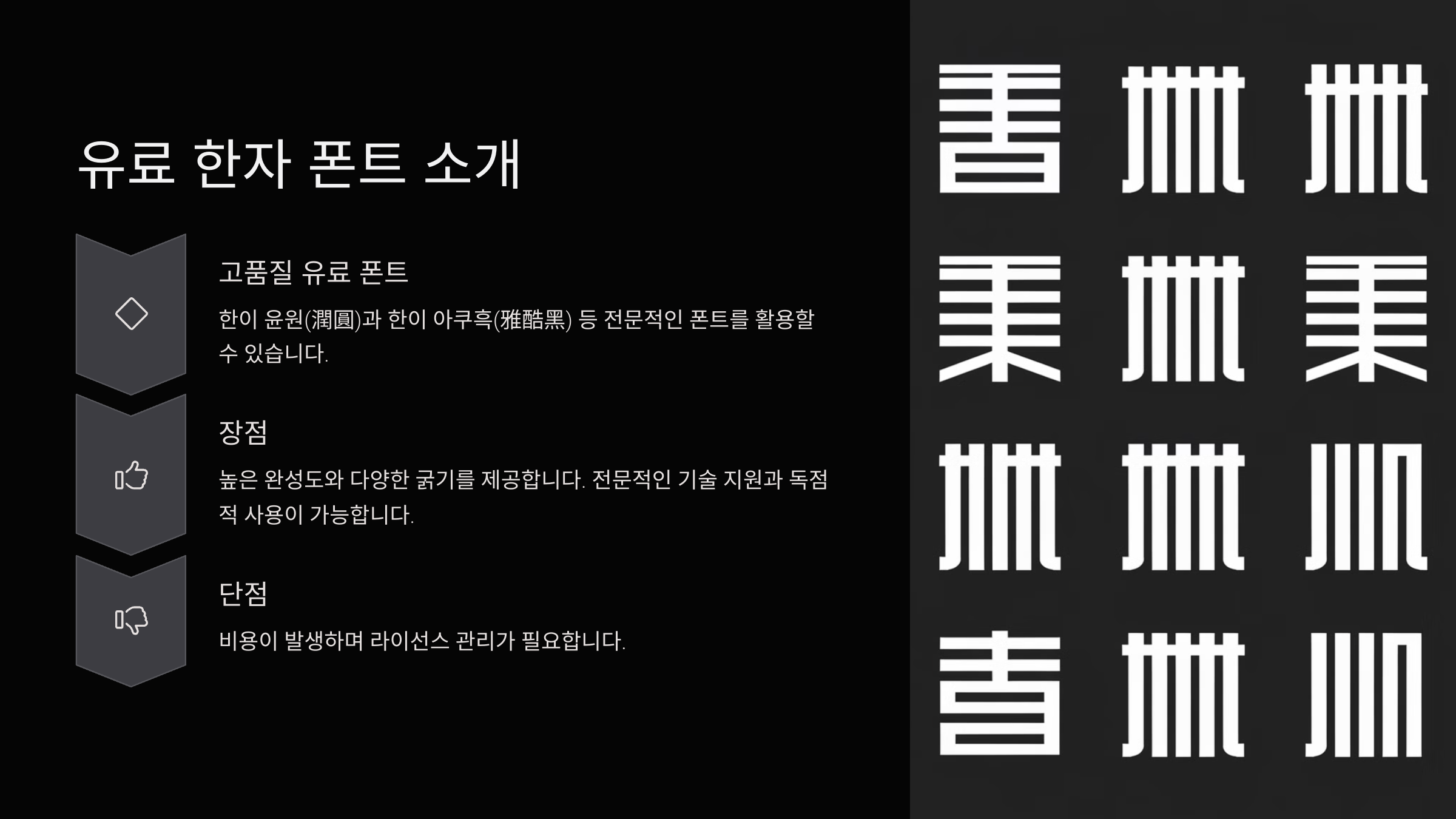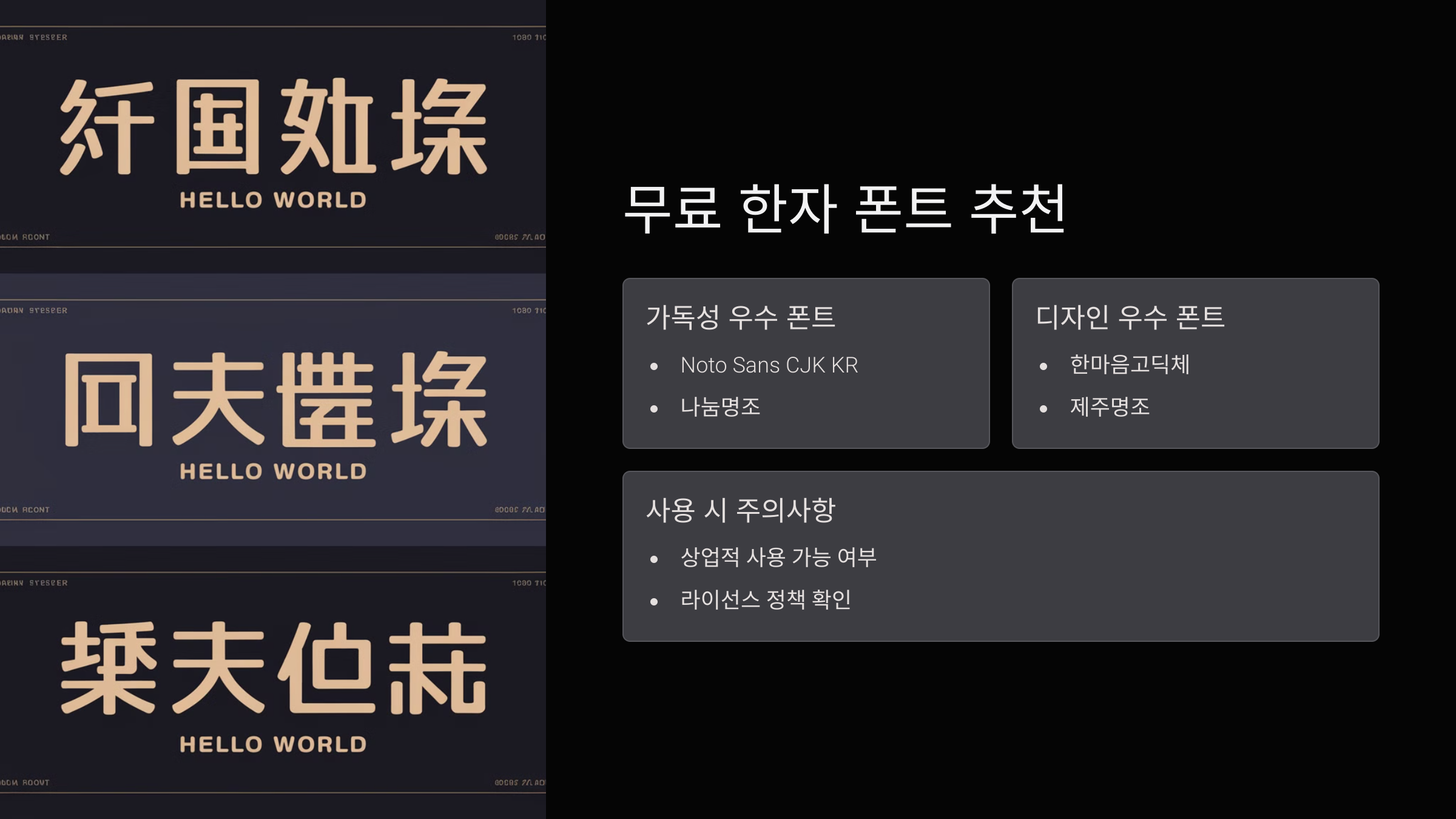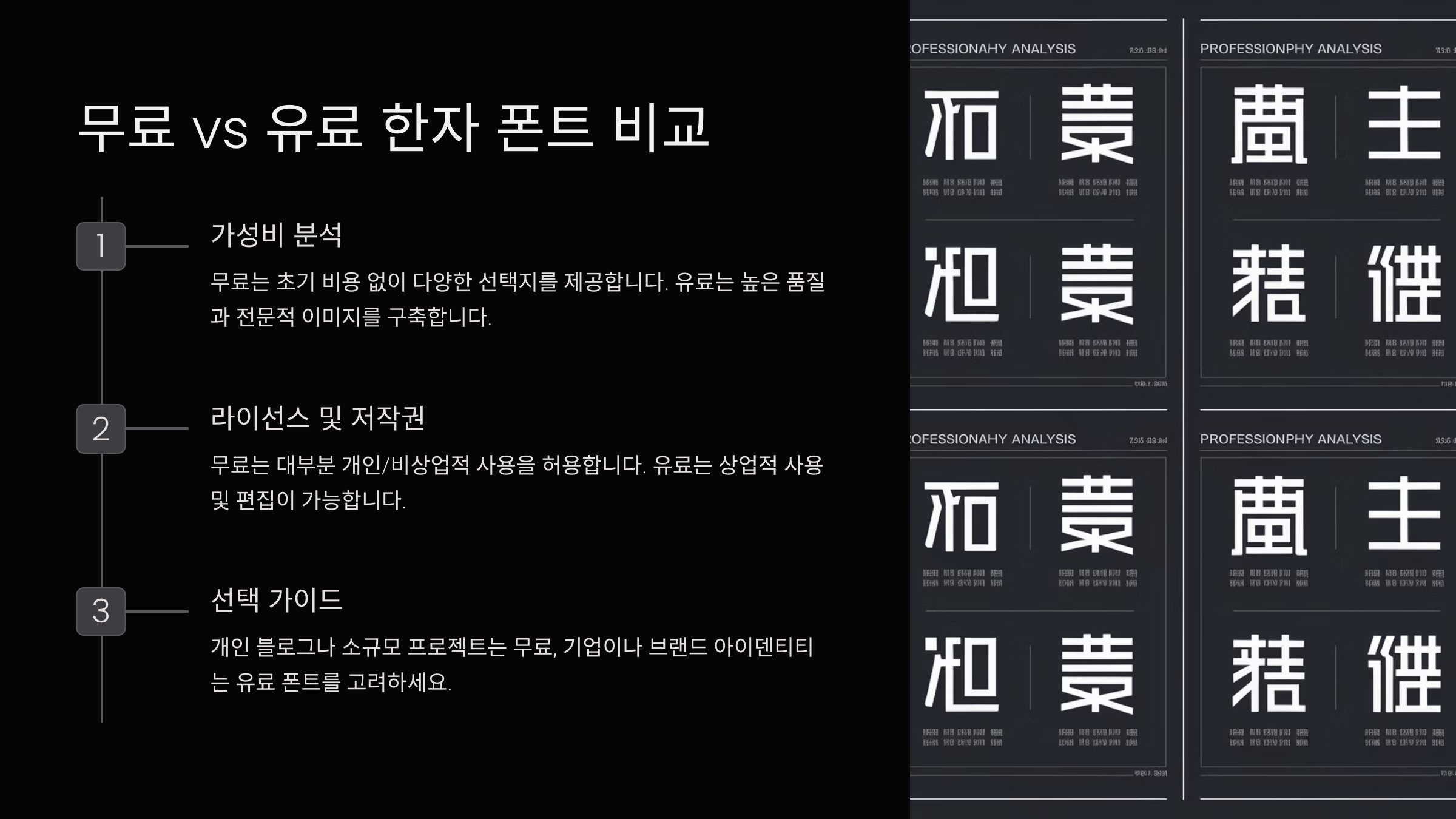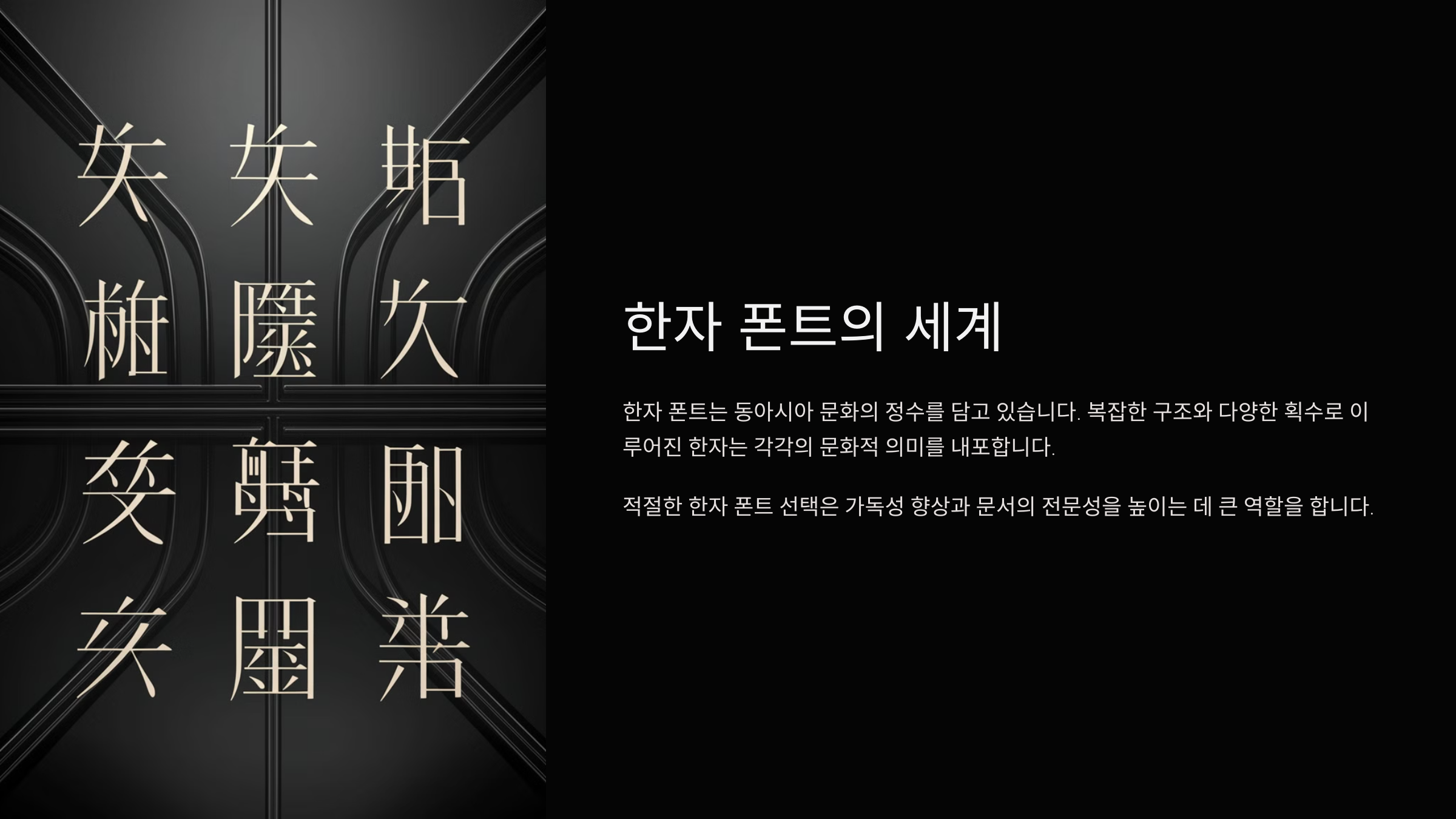
ํ•œ์ž ํฐํŠธ ์ถ”์ฒœ! ๋ฌด๋ฃŒ vs ์œ ๋ฃŒ, ์–ด๋–ค ๊ฒƒ์ด ๋” ์ข‹์„๊นŒ?
ํ•œ์ž ํฐํŠธ๋ž€?
ํ•œ์ž ํฐํŠธ์˜ ํŠน์ง•
ํ•œ์ž ํฐํŠธ๋Š” ๋ณต์žกํ•œ ํš๊ณผ ๋‹ค์–‘ํ•œ ๊ธ€์ž ํฌ๊ธฐ๋กœ ์ธํ•ด ์ผ๋ฐ˜์ ์ธ ํฐํŠธ๋ณด๋‹ค ์ •๊ตํ•œ ๋””์ž์ธ์ด ํ•„์š”ํ•ฉ๋‹ˆ๋‹ค. ํŠนํžˆ ๊ฐ€๋…์„ฑ๊ณผ ๋ฏธ์ ์ธ ์š”์†Œ๋ฅผ ๋™์‹œ์— ๊ณ ๋ คํ•ด์•ผ ํ•˜๋ฉฐ, ์†๊ธ€์”จ ์Šคํƒ€์ผ๊ณผ ๊ณ ๋”•์ฒด, ๋ช…์กฐ์ฒด ๋“ฑ ๋‹ค์–‘ํ•œ ์œ ํ˜•์ด ์กด์žฌํ•ฉ๋‹ˆ๋‹ค.
ํ•œ์ž ํฐํŠธ์˜ ์ค‘์š”์„ฑ
ํ•œ์ž ํฐํŠธ๋Š” ๋ฌธ์„œ์˜ ์ „๋ฌธ์„ฑ๊ณผ ์‹ ๋ขฐ๋„๋ฅผ ๋†’์ด๋Š” ์ค‘์š”ํ•œ ์—ญํ• ์„ ํ•ฉ๋‹ˆ๋‹ค. ํŠนํžˆ ์ „ํ†ต์ ์ธ ๋А๋‚Œ์„ ์‚ด๋ฆฌ๊ฑฐ๋‚˜ ๊ณต์‹ ๋ฌธ์„œ์—์„œ ์‚ฌ์šฉ๋  ๊ฒฝ์šฐ ์ ์ ˆํ•œ ํฐํŠธ ์„ ํƒ์ด ํ•„์ˆ˜์ ์ž…๋‹ˆ๋‹ค.
ํ•œ์ž ํฐํŠธ์˜ ํ™œ์šฉ ๋ถ„์•ผ
ํ•œ์ž ํฐํŠธ๋Š” ์ถœํŒ, ๊ต์œก ์ž๋ฃŒ, ์ „ํ†ต ์˜ˆ์ˆ  ๋””์ž์ธ, ๋ธŒ๋žœ๋“œ ๋กœ๊ณ , ์›น์‚ฌ์ดํŠธ ๋ฐ ์•ฑ UI ๋“ฑ ๋‹ค์–‘ํ•œ ๋ถ„์•ผ์—์„œ ์‚ฌ์šฉ๋ฉ๋‹ˆ๋‹ค. ํŠนํžˆ ๊ฐ€๋…์„ฑ์ด ์ค‘์š”ํ•œ ๋ฒ•๋ฅ  ๋ฌธ์„œ๋‚˜ ๋…ผ๋ฌธ์—์„œ๋Š” ๋ช…์กฐ์ฒด ๊ณ„์—ด์ด ์ฃผ๋กœ ํ™œ์šฉ๋ฉ๋‹ˆ๋‹ค.
ํ•ญ๋ชฉ ์„ค๋ช…
ํฐํŠธ ์œ ํ˜• ๋ช…์กฐ์ฒด, ๊ณ ๋”•์ฒด, ์†๊ธ€์”จ์ฒด ๋“ฑ
์ฃผ์š” ํŠน์ง• ํš์ด ๋งŽ๊ณ  ๋ณต์žกํ•œ ๊ตฌ์กฐ
ํ™œ์šฉ ๋ถ„์•ผ ์ถœํŒ, ๊ต์œก, ๋ธŒ๋žœ๋“œ ๋กœ๊ณ , ์›น๋””์ž์ธ
๋ฌด๋ฃŒ ํ•œ์ž ํฐํŠธ ์ถ”์ฒœ
๊ฐ€๋…์„ฑ์ด ๋›ฐ์–ด๋‚œ ๋ฌด๋ฃŒ ํฐํŠธ
๋ฌด๋ฃŒ ํ•œ์ž ํฐํŠธ ์ค‘์—์„œ๋„ ๊ฐ€๋…์„ฑ์ด ๋›ฐ์–ด๋‚œ ํฐํŠธ๊ฐ€ ๋งŽ์Šต๋‹ˆ๋‹ค. ๋Œ€ํ‘œ์ ์œผ๋กœ 'Noto Sans CJK', 'Source Han Serif' ๋“ฑ์ด ์žˆ์œผ๋ฉฐ, ์ด๋“ค์€ ์ž‘์€ ๊ธ€์”จ์—์„œ๋„ ์„ ๋ช…ํ•˜๊ฒŒ ๋ณด์ด๋ฉฐ ๋‹ค์–‘ํ•œ ๋ฌธ์„œ ์ž‘์—…์— ์ ํ•ฉํ•ฉ๋‹ˆ๋‹ค.
๋””์ž์ธ์ด ์šฐ์ˆ˜ํ•œ ๋ฌด๋ฃŒ ํฐํŠธ
๋””์ž์ธ์ ์œผ๋กœ ์•„๋ฆ„๋‹ค์šด ๋ฌด๋ฃŒ ํ•œ์ž ํฐํŠธ๋กœ๋Š” 'Zen Kaku Gothic', 'I.Ming' ๋“ฑ์ด ์žˆ์Šต๋‹ˆ๋‹ค. ์ด ํฐํŠธ๋“ค์€ ์ „ํ†ต์ ์ธ ๋А๋‚Œ์„ ์œ ์ง€ํ•˜๋ฉด์„œ๋„ ํ˜„๋Œ€์ ์ธ ์š”์†Œ๋ฅผ ๊ฐ€๋ฏธํ•œ ์Šคํƒ€์ผ์„ ์ œ๊ณตํ•ฉ๋‹ˆ๋‹ค.
ํฐํŠธ๋ช… ํŠน์ง•
Noto Sans CJK ๊ตฌ๊ธ€ ์ œ๊ณต, ๋‹ค์–‘ํ•œ ํฌ๊ธฐ์—์„œ๋„ ์„ ๋ช…
Source Han Serif ์„ธ๋ฆฌํ”„ ์Šคํƒ€์ผ, ๋ฌธ์„œ ์ž‘์—…์— ์ ํ•ฉ
Zen Kaku Gothic ๋ชจ๋˜ํ•œ ๋””์ž์ธ, UI/UX์— ์ ํ•ฉ
์œ ๋ฃŒ ํ•œ์ž ํฐํŠธ ์ถ”์ฒœ
๊ณ ํ’ˆ์งˆ ์œ ๋ฃŒ ํฐํŠธ ์†Œ๊ฐœ
์œ ๋ฃŒ ํ•œ์ž ํฐํŠธ๋Š” ๋””์ž์ธ์˜ ์ •๊ตํ•จ๊ณผ ๊ฐ€๋…์„ฑ์ด ๋›ฐ์–ด๋‚˜๋ฉฐ, ๋ธŒ๋žœ๋“œ ์•„์ด๋ดํ‹ฐํ‹ฐ๋ฅผ ๊ฐ•ํ™”ํ•˜๋Š” ๋ฐ ์œ ๋ฆฌํ•ฉ๋‹ˆ๋‹ค. ๋Œ€ํ‘œ์ ์ธ ์œ ๋ฃŒ ํฐํŠธ๋กœ๋Š” ‘๋ชจ๋ฆฌ์‚ฌ์™€(Morisawa)’, ‘ํžˆ๋ผ๊ธฐ๋…ธ(Hiragino)’, ‘๋‹ค์ด์š” ํƒ€์ดํฌ(Dynacomware)’ ๋“ฑ์ด ์žˆ์œผ๋ฉฐ, ์ผ๋ณธ๊ณผ ์ค‘๊ตญ์˜ ๋Œ€ํ˜• ์ถœํŒ์‚ฌ์—์„œ๋„ ๋„๋ฆฌ ์‚ฌ์šฉ๋ฉ๋‹ˆ๋‹ค.
์œ ๋ฃŒ ํฐํŠธ์˜ ์žฅ์ 
์œ ๋ฃŒ ํ•œ์ž ํฐํŠธ๋Š” ๊ธ€์ž ๊ฐ„๊ฒฉ์ด ์ •๋ฐ€ํ•˜๊ฒŒ ์กฐ์ •๋˜์–ด ์žˆ์–ด ์ธ์‡„๋ฌผ, ์›น๋””์ž์ธ, ์•ฑ UI์—์„œ ์™„์„ฑ๋„ ๋†’์€ ๊ฒฐ๊ณผ๋ฌผ์„ ์ œ๊ณตํ•ฉ๋‹ˆ๋‹ค. ๋˜ํ•œ ๋‹ค์–‘ํ•œ ๊ตต๊ธฐ์™€ ์Šคํƒ€์ผ์ด ์ง€์›๋˜์–ด ๋‹ค์–‘ํ•œ ์ฝ˜ํ…์ธ  ์ œ์ž‘์— ํ™œ์šฉํ•˜๊ธฐ ์ข‹์Šต๋‹ˆ๋‹ค.
์œ ๋ฃŒ ํฐํŠธ์˜ ๋‹จ์ 
ํฐํŠธ๋ช… ํŠน์ง•
๋ชจ๋ฆฌ์‚ฌ์™€ ์ผ๋ณธ ์ถœํŒ์—…๊ณ„์—์„œ ๋„๋ฆฌ ์‚ฌ์šฉ, ์ •๊ตํ•œ ๊ธ€์ž ๋””์ž์ธ
ํžˆ๋ผ๊ธฐ๋…ธ ์• ํ”Œ macOS ๊ธฐ๋ณธ ํ•œ์ž ํฐํŠธ, ๋ฏธ๋ คํ•œ ๋””์ž์ธ
๋‹ค์ด์š” ํƒ€์ดํฌ ๋‹ค์–‘ํ•œ ์Šคํƒ€์ผ ์ œ๊ณต, ์›น ๋ฐ ์ธ์‡„์— ์ตœ์ ํ™”
๋ฌด๋ฃŒ vs ์œ ๋ฃŒ ํ•œ์ž ํฐํŠธ ๋น„๊ต
๊ฐ€์„ฑ๋น„ ๋ถ„์„
๋ฌด๋ฃŒ ํ•œ์ž ํฐํŠธ๋Š” ๋น„์šฉ ๋ถ€๋‹ด ์—†์ด ์‚ฌ์šฉํ•  ์ˆ˜ ์žˆ์ง€๋งŒ, ์Šคํƒ€์ผ์˜ ๋‹ค์–‘์„ฑ์ด ๋ถ€์กฑํ•  ์ˆ˜ ์žˆ์Šต๋‹ˆ๋‹ค. ๋ฐ˜๋ฉด ์œ ๋ฃŒ ํฐํŠธ๋Š” ์™„์„ฑ๋„๊ฐ€ ๋†’๊ณ  ๋‹ค์–‘ํ•œ ์„œ์ฒด๋ฅผ ์ œ๊ณตํ•˜์ง€๋งŒ, ์ƒ๋‹นํ•œ ๋น„์šฉ์ด ๋ฐœ์ƒํ•  ์ˆ˜ ์žˆ์Šต๋‹ˆ๋‹ค. ํ”„๋กœ์ ํŠธ์˜ ์˜ˆ์‚ฐ๊ณผ ๋ชฉ์ ์„ ๊ณ ๋ คํ•ด ์„ ํƒํ•˜๋Š” ๊ฒƒ์ด ์ค‘์š”ํ•ฉ๋‹ˆ๋‹ค.
๋ผ์ด์„ ์Šค ๋ฐ ์ €์ž‘๊ถŒ ๋ฌธ์ œ
๋ฌด๋ฃŒ ํฐํŠธ๋ผ๋„ ์ผ๋ถ€๋Š” ๊ฐœ์ธ ์‚ฌ์šฉ๋งŒ ๊ฐ€๋Šฅํ•˜๊ณ , ์ƒ์—…์  ์‚ฌ์šฉ์—๋Š” ์ œํ•œ์ด ์žˆ์„ ์ˆ˜ ์žˆ์Šต๋‹ˆ๋‹ค. ์œ ๋ฃŒ ํฐํŠธ์˜ ๊ฒฝ์šฐ ๊ตฌ๋งคํ•œ ๋ผ์ด์„ ์Šค์— ๋”ฐ๋ผ ์‚ฌ์šฉ ๋ฒ”์œ„๊ฐ€ ์ •ํ•ด์ง€๋ฏ€๋กœ ๋ฐ˜๋“œ์‹œ ๊ณ„์•ฝ ์กฐ๊ฑด์„ ํ™•์ธํ•ด์•ผ ํ•ฉ๋‹ˆ๋‹ค.
์‚ฌ์šฉ ๋ชฉ์ ์— ๋”ฐ๋ฅธ ์„ ํƒ ๊ฐ€์ด๋“œ
Q6: ํ•œ์ž ํฐํŠธ์˜ ํŒŒ์ผ ํ˜•์‹์€ ๋ฌด์—‡์ธ๊ฐ€์š”?
A: ์ผ๋ฐ˜์ ์œผ๋กœ ์‚ฌ์šฉ๋˜๋Š” ํ•œ์ž ํฐํŠธ ํŒŒ์ผ ํ˜•์‹์€ TTF(TrueType), OTF(OpenType), WOFF(Web Open Font Format) ๋“ฑ์ด ์žˆ์Šต๋‹ˆ๋‹ค. ์›น์—์„œ๋Š” WOFF2 ํ˜•์‹์ด ์ตœ์ ํ™”๋˜์–ด ์žˆ์Šต๋‹ˆ๋‹ค.